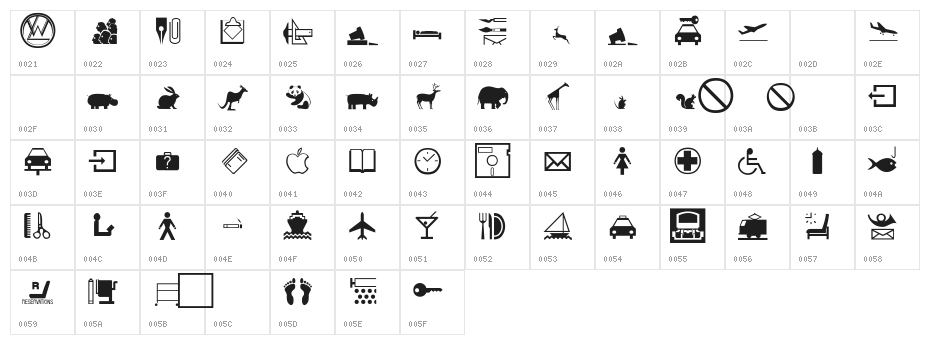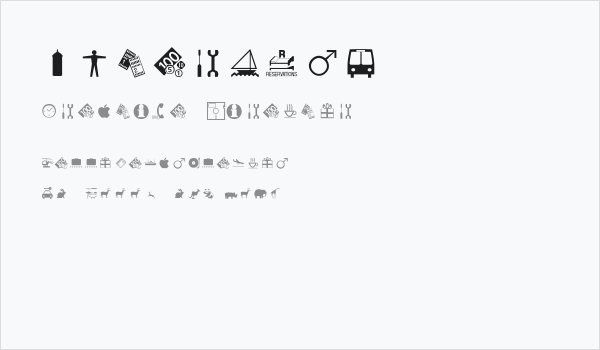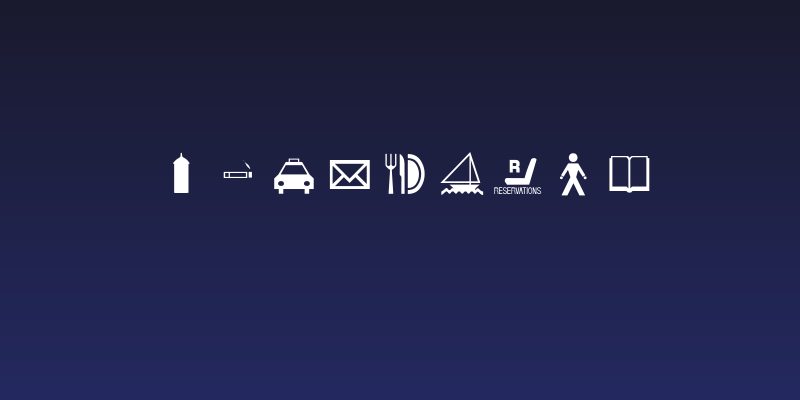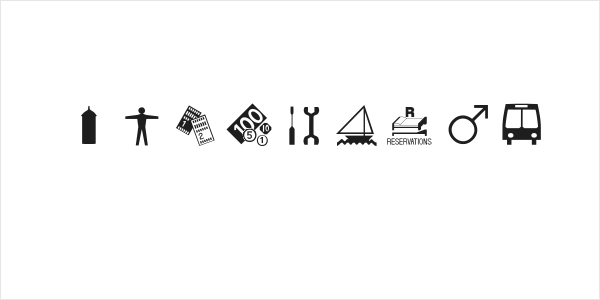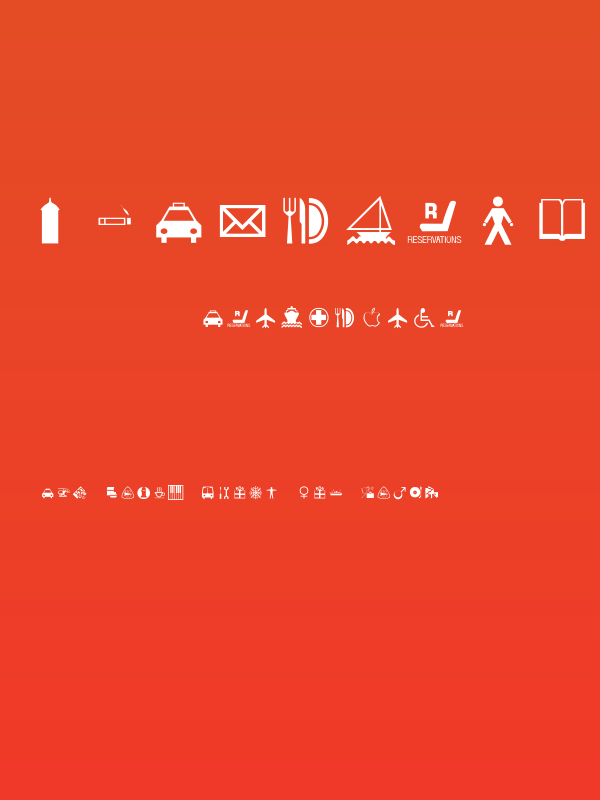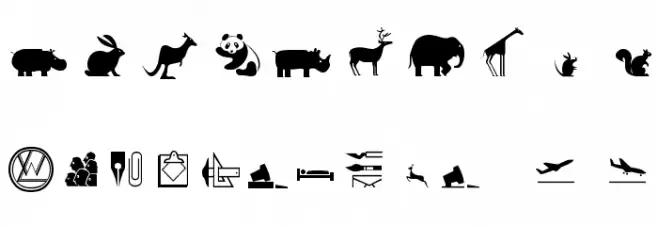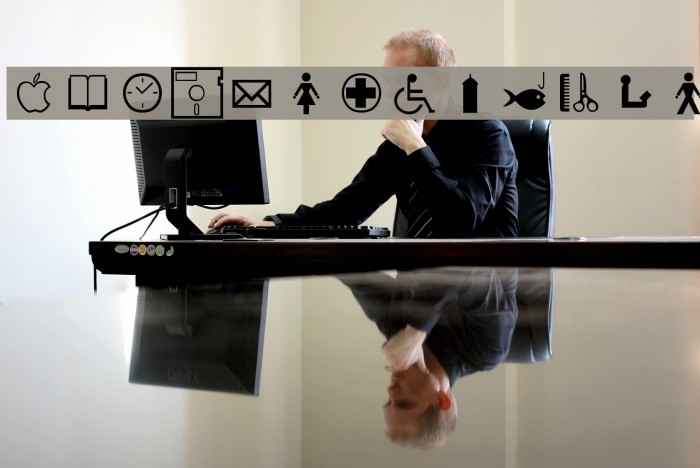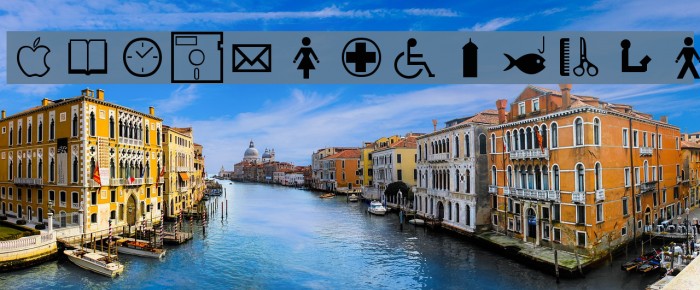
InterSymb Font
| Gesamtstil | Modern, Minimalist, Functional |
| Anwendungsfall | Signage, Icons, Infographics, User Interfaces |
| Vorgeschlagene Projekte | Wayfinding signage, transportation maps, infographics, instructional materials, mobile app UI, public space labeling. |